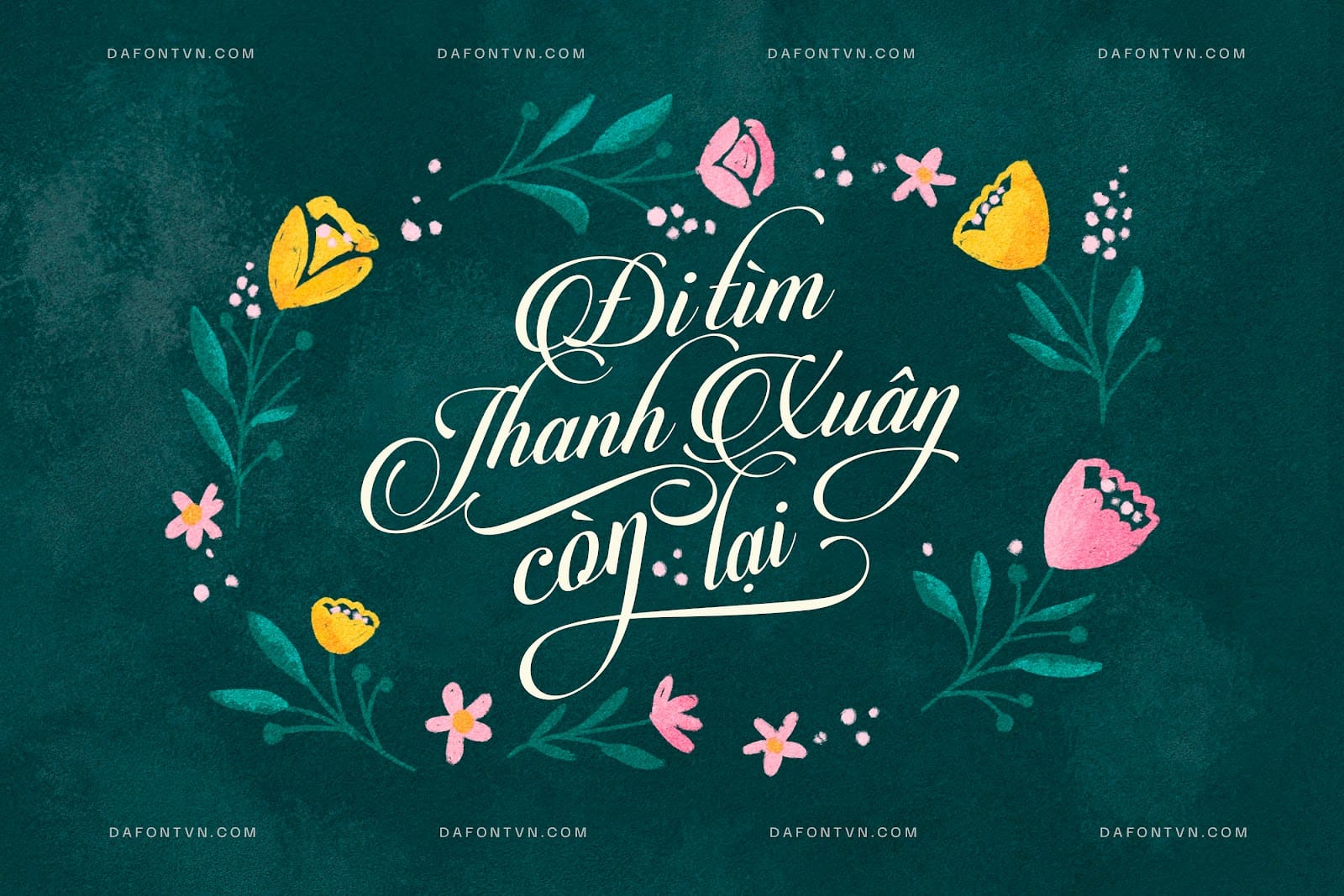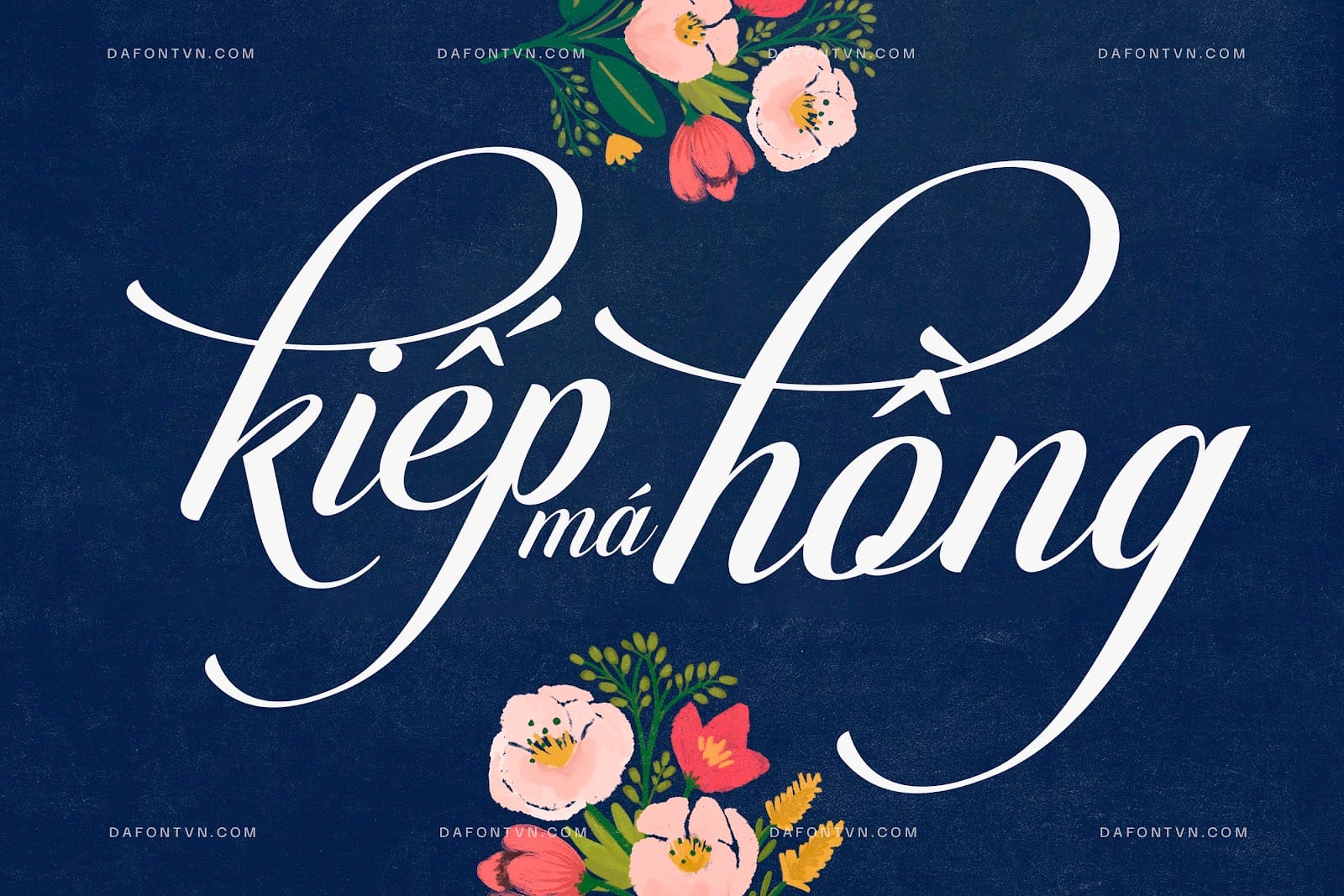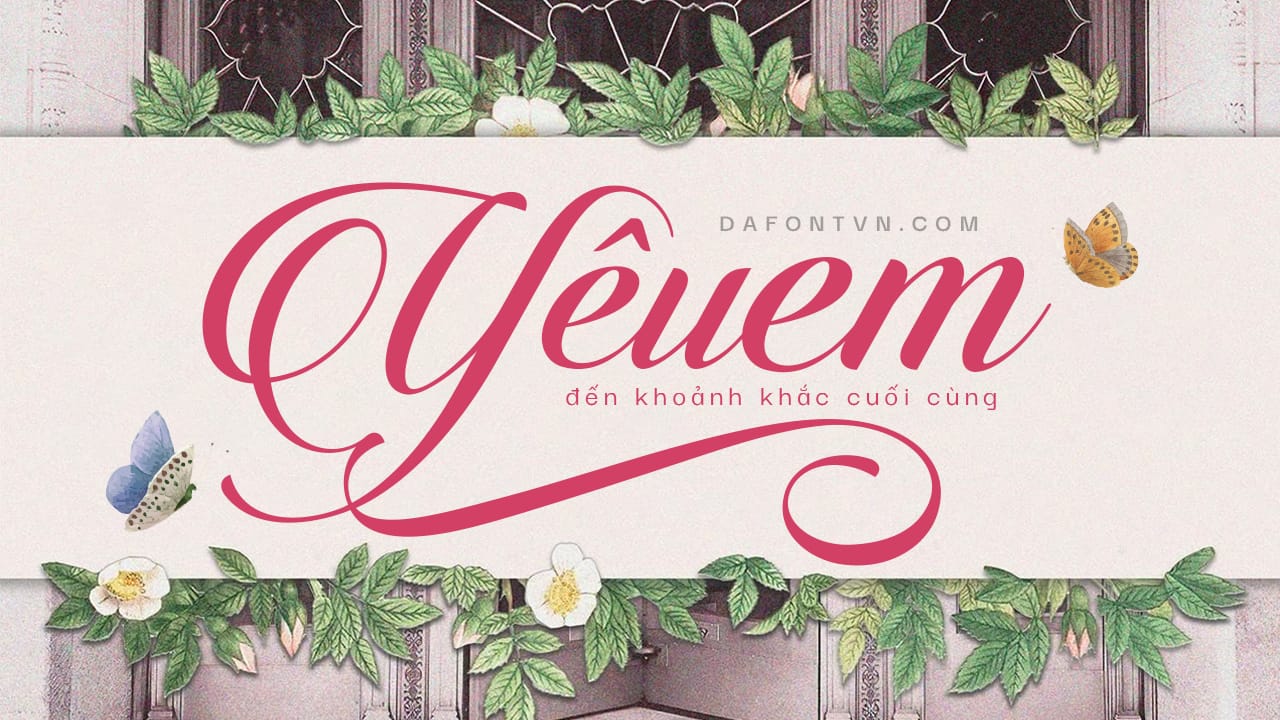
Candlescript Pro Font là kiểu phông chữ viết tay ấn tượng. Phần nội dung của font Candlescript đã được thiết kế với độ chi tiết cao, chính xác, mượt mà và tuyệt đẹp, vì vậy bạn có thể sử dụng nó cho nhiều mục đích thiết kế khác nhau như biểu trưng, tiêu đề, bìa sách, tạp chí, thiệp mời, quảng cáo, chữ thiệp cưới…
Đặc biệt Candlescript Pro có tới hơn 2850 glyph bao gồm chữ viết hoa, chữ viết thường, chữ hoa nhỏ, chữ số, phân số, dấm chấm câu và hầu hết các glyph khác với các biến thể là một phần của tính năng OpenType chẳng hạn như Chữ ghép tiêu chuẩn (Standard Ligatures), Chữ ghép tùy ý (Discretionary Ligatures), Chữ thay thế kiểu cách (Stylistic Alternates), Chữ thay thế theo ngữ cảnh (Contextual Alternates), Chữ thay thế tiêu đề (Titling Alternates) và hàng nghìn ký tự swashes.
Candlescript cũng rất dễ để kết hợp với các phông chữ Serif, Sans Serif hay Slab Serif. Vì vậy font Candlescript trở thành một trong những tùy chọn phông chữ hiển thị đa chức năng và chắn chắn sẽ làm đẹp bố cục và trông rất chuyên nghiệp trong các thiết kế của bạn.
Các tính năng OpenType không hoạt động tự động, nhưng bạn có thể truy cập bằng cách thủ công và để có được kết quả tốt nhất trong các thiết kế, bạn cần có sự sáng tạo trong việc kết hợp các biến thể Glyph này.
Font Candlescript Pro Việt hóa đầy đủ, chỉnh sửa, tối ưu và kerning, ngoài ra bộ font còn bao gồm các part để bạn vẫn có thể truy cập tổng thể các biến thể Glyph nếu chương trình của bạn không hỗ trợ các tính năng OpenType và bảng Glyph.